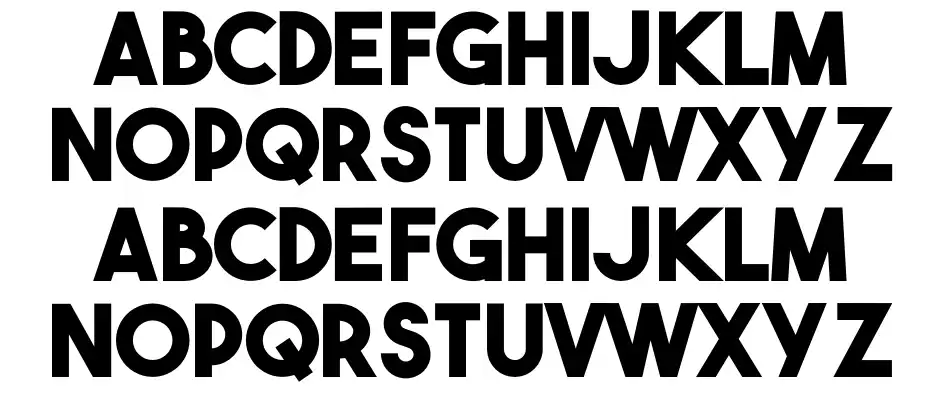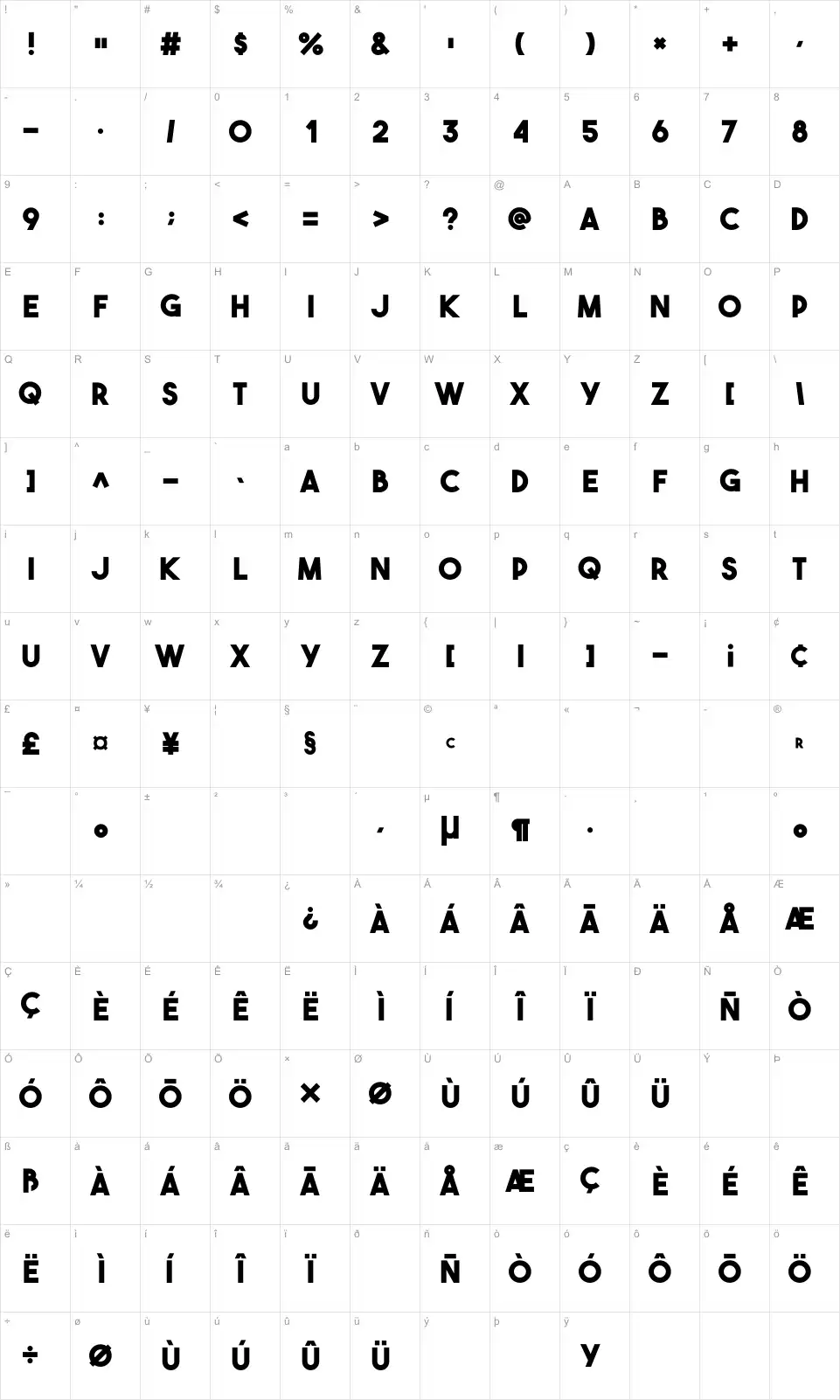
A fonte The Bold Font, criada por Pindarots, é uma opção simples e moderna para sua necessidade de tipo. Para aqueles que buscam uma fonte básica e elegante, essa é uma escolha ótima. Licenciada sob uma licença livre, o The Bold Font é disponível em formato TTF, adequado para uso em diversos projetos digitais. Pertencendo à categoria Basic > Sans Serif, a The Bold Font combina facilidade de uso com estilo, tornando-a uma escolha popular para designers e criadores de conteúdo que buscam uma fonte básica e moderna. Com um tamanho de arquivo de apenas 15 KB e 11.695 downloads únicos, é fácil encontrar e incorporar essa fonte em seu projeto. A Pindarots, o designer responsável pela The Bold Font, oferece mais detalhes em seu site, www.pindarots.com. Experimente o preview de texto personalizado para ver como a The Bold Font se destaca, sem comprometer seu projeto. Sem dúvida, essa fonte é um recurso útil para quem está buscando um tipo básico e moderno.
Designer: Pindarots’